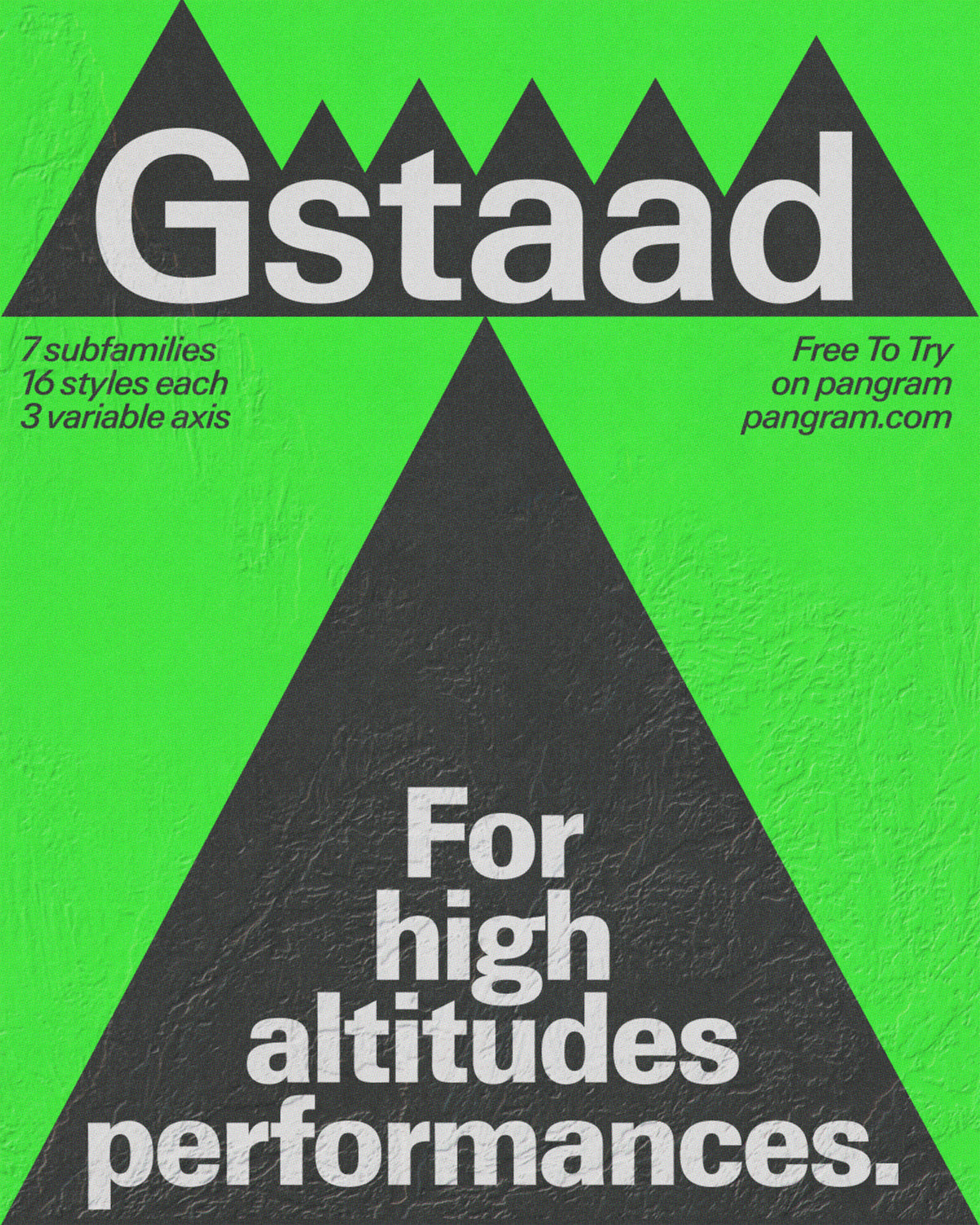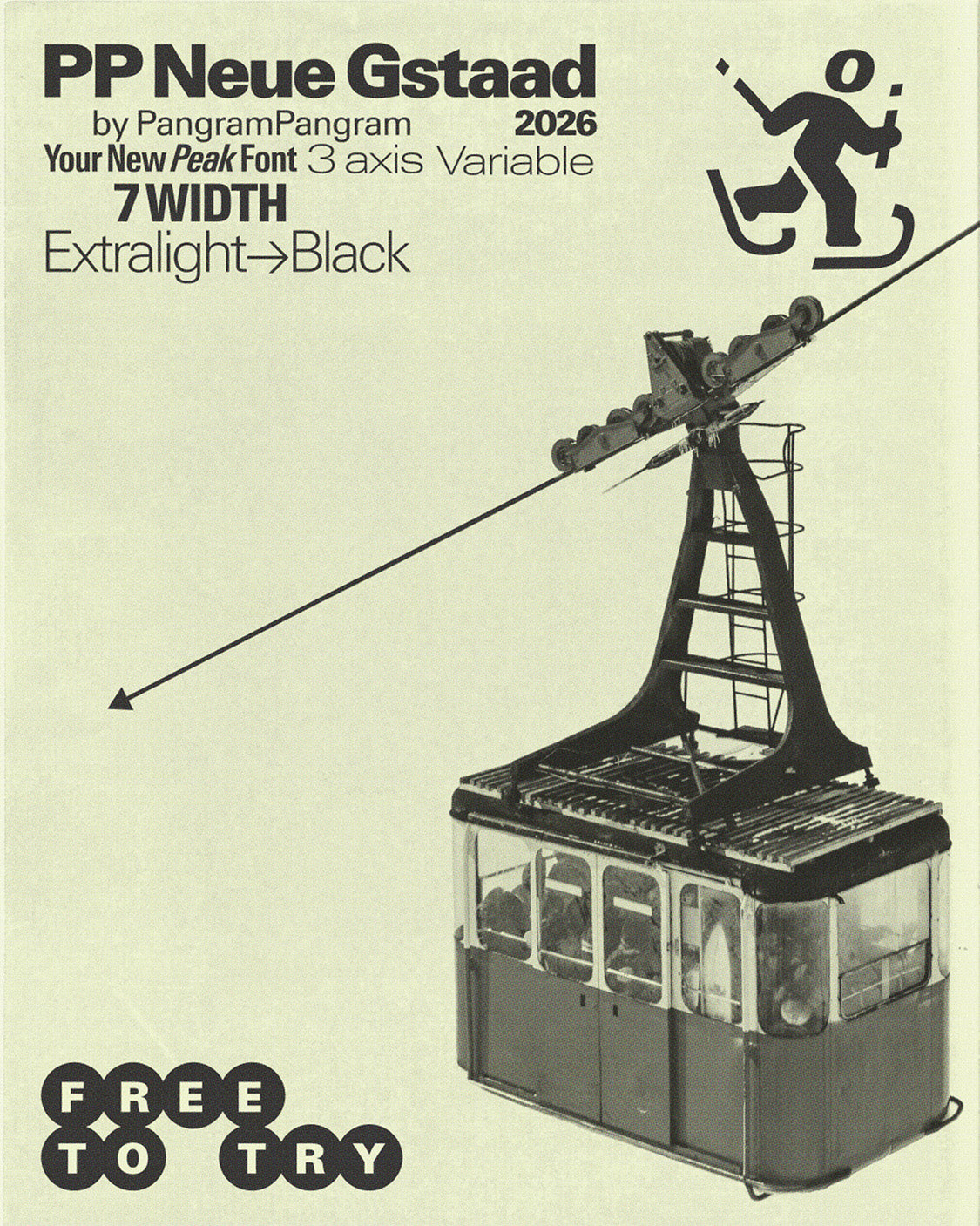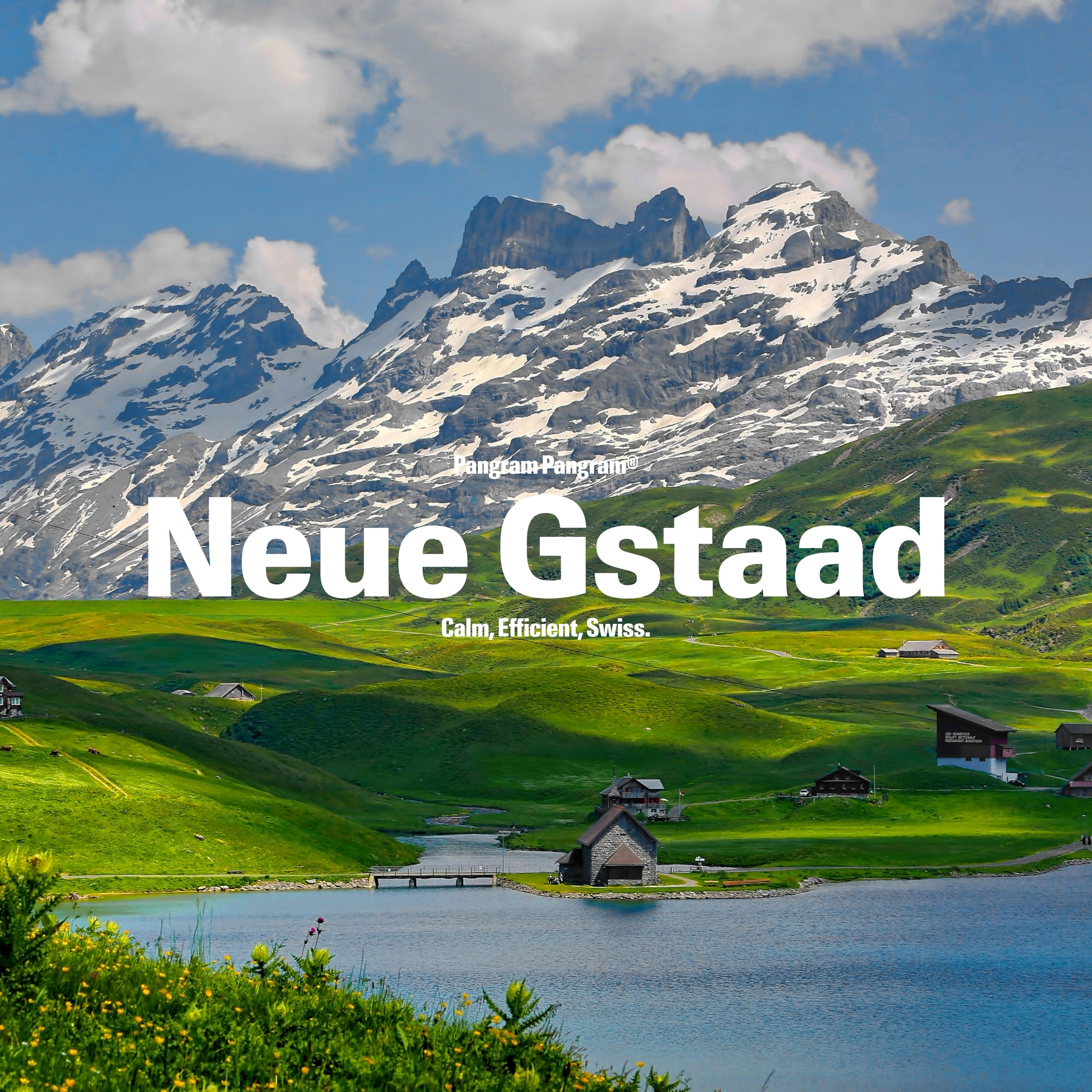
Neue Gstaad Compact
A Swiss sense of refinement.
Neue Gstaad Compact
Inspired by typographic giants, Neue Gstaad interprets its references with restraint.
Neue Gstaad Compact
Its structure unfolds across an ultra-versatile variable system, spanning from Compressed to Expanded, allowing for a fluid range of voices, from compact editorial settings to expansive, architectural compositions. Neue Gstaad evokes a sensibility rather than a location. It suggests altitude without excess, luxury without noise, a cultivated balance between tradition and modernity, discipline and openness.
Neue Gstaad Compact
Neue Gstaad is a contemporary type family shaped by a distinctly Swiss sense of refinement, calm, confidence, and precision. Designed by Ian Party, it moves beyond regional clichés to embrace a broader, more universal expression of Swiss design: one rooted in clarity, discretion, and quiet sophistication. Loosely inspired by typographic giants, Neue Gstaad interprets its references with restraint. Its structure unfolds across an ultra-versatile variable system, spanning from Compressed to Expanded, allowing for a fluid range of voices, from compact editorial settings to expansive, architectural compositions. Neue Gstaad evokes a sensibility rather than a location. It suggests altitude without excess, luxury without noise, a cultivated balance between tradition and modernity, discipline and openness. The family includes 112 styles, 7 subfamilies, and is built as a complete, future-facing typographic system. It is rich in OpenType features and supports a wide range of Latin-based languages. Rooted in heritage yet designed for the future, Neue Gstaad reflects Ian Party’s ongoing exploration of type as a living system. It is a rich and complex design distilled into an essential clarity, where simplicity emerges not from reduction, but from mastery. A new stage in the development of a complete variable ecosystem, Neue Gstaad embodies a singular idea: a quiet form of expression, shaped by precision.
Alternate g
g
→
g
Alternate Q
Q
→
Q
Alternate a
a
→
a
Round Dots
:;ijë...!?
Alternate 6 9
6 9
→
6 9
Standard Ligatures
fi fl ff ffi ffl
Case-Sensitive Forms
(11:11) - [2] H—H
Calme. Efficace. Suisse.
Neue Gstaad est une famille de caractères contemporaine, façonnée par un sens nettement suisse du raffinement, du calme, de la confiance et de la précision. Conçue par Ian Party, elle dépasse les clichés régionaux pour embrasser une expression plus large et plus universelle du design suisse : une expression enracinée dans la clarté, la discrétion et une sophistication discrète. Lâchement inspirée par des géants typographiques, Neue Gstaad interprète ses références avec retenue. Sa structure se déploie à travers un système variable ultra-polyvalent, allant de Compressed à Expanded, permettant une gamme fluide de voix, des paramètres éditoriaux compacts aux compositions architecturales étendues.
Neue Gstaad évoque une sensibilité plutôt qu'un lieu. Elle suggère l'altitude sans excès, le luxe sans bruit, un équilibre cultivé entre tradition et modernité, discipline et ouverture. La famille comprend 112 styles, 7 sous-familles, et est conçue comme un système typographique complet et tourné vers l'avenir. Elle est riche en fonctionnalités OpenType et prend en charge un large éventail de langues basées sur le latin.
Enracinée dans l'héritage mais conçue pour l'avenir, Neue Gstaad reflète l'exploration continue de Ian Party de la typographie en tant que système vivant. C'est un design riche et complexe distillé dans une clarté essentielle, où la simplicité n'émerge pas de la réduction, mais de la maîtrise.
Nouvelle étape dans le développement d'un écosystème variable complet, Neue Gstaad incarne une idée singulière : une forme d'expression discrète, façonnée par la précision.
16 graisses avec 548 glyphes chacune
Italiques inclus